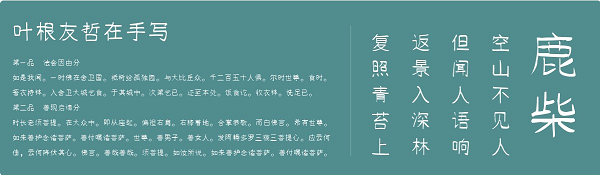
葉根友哲在手寫字體是由葉根友全新發(fā)布的一款手寫字體,該字體維系一貫的手寫字體特色,字里行間帶有一絲絲文雅舒適感,能夠讓用戶獲得一首完美的字體,喜歡的用戶快來綠色資源網(wǎng)下載吧!
葉根友哲在手寫是葉根友字庫全新開發(fā)的一款優(yōu)雅的手寫體,該字體筆畫設(shè)計(jì)中融入了書寫的韻味,講究線條之美,使筆劃挺拔有力,剛?cè)嵯酀?jì)筆畫粗壯有力,能夠應(yīng)用于文本裝潢、信息展示、網(wǎng)頁設(shè)計(jì)、篆刻制模、數(shù)據(jù)制作、裝潢設(shè)計(jì)、計(jì)算藝術(shù)設(shè)計(jì)、視覺設(shè)計(jì)、字帖等一切合法應(yīng)用場景,有喜歡的朋友可免費(fèi)下載收藏。